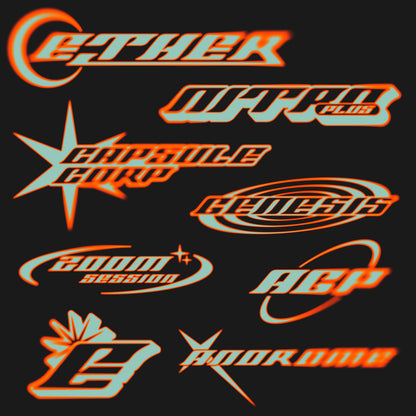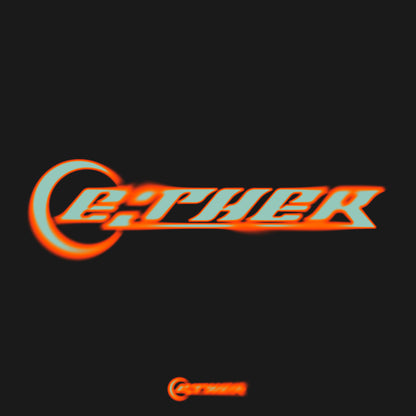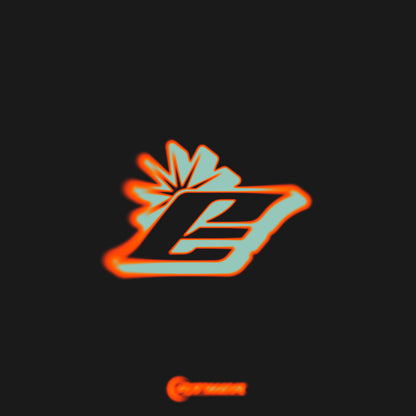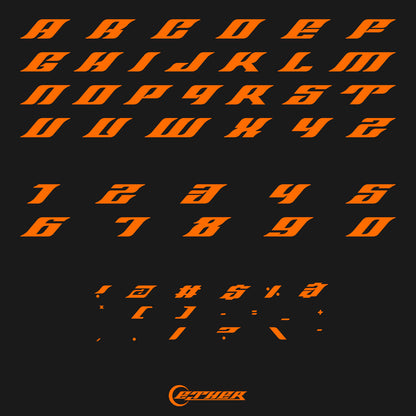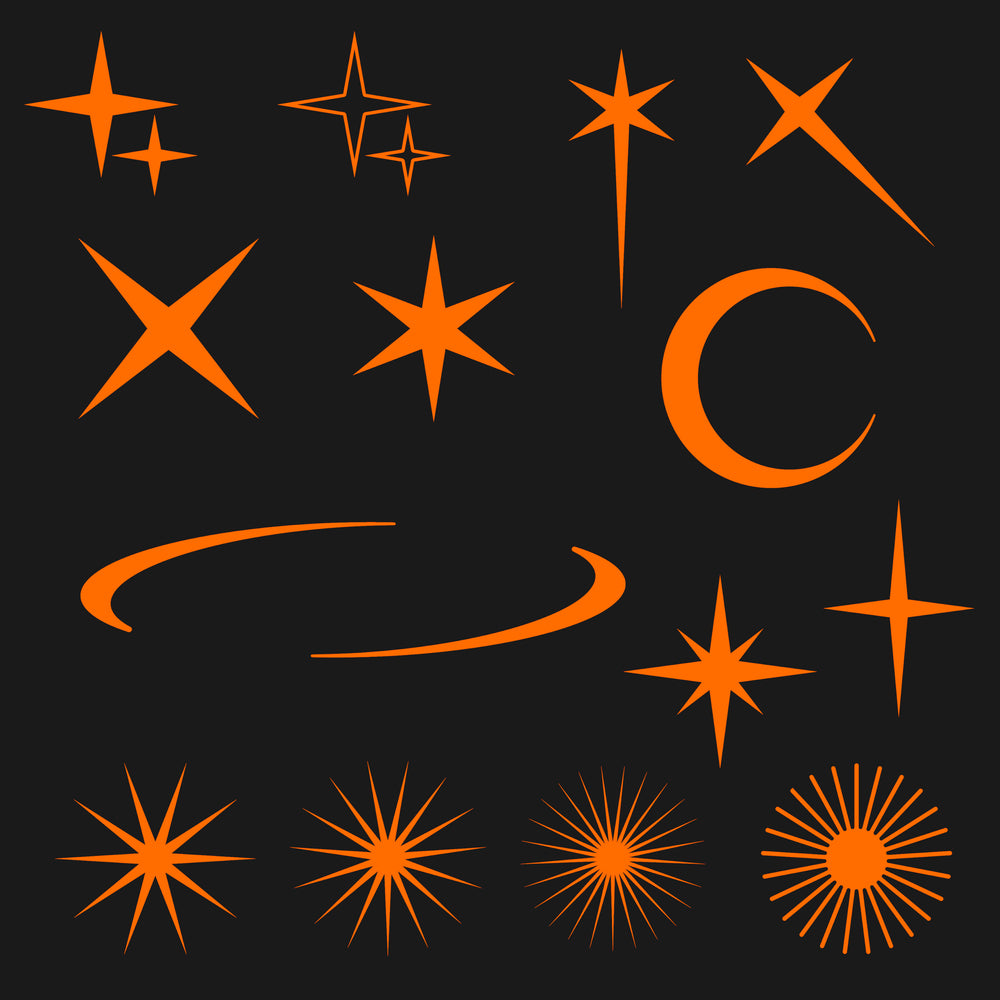
ETHER - Typeface
Découvrez Hvnter, la police de caractères conçue par le talentueux créateur du même nom.
Cette police polyvalente comprend :
L'alphabet complet en majuscules et minuscules (A-Z, a-z).
Les chiffres de 0 à 9.
Un ensemble de symboles.
Idéale pour le branding, les affiches ou tout autre projet de design, la police Hvnter vous offre un large éventail d'options pour donner vie à vos idées.